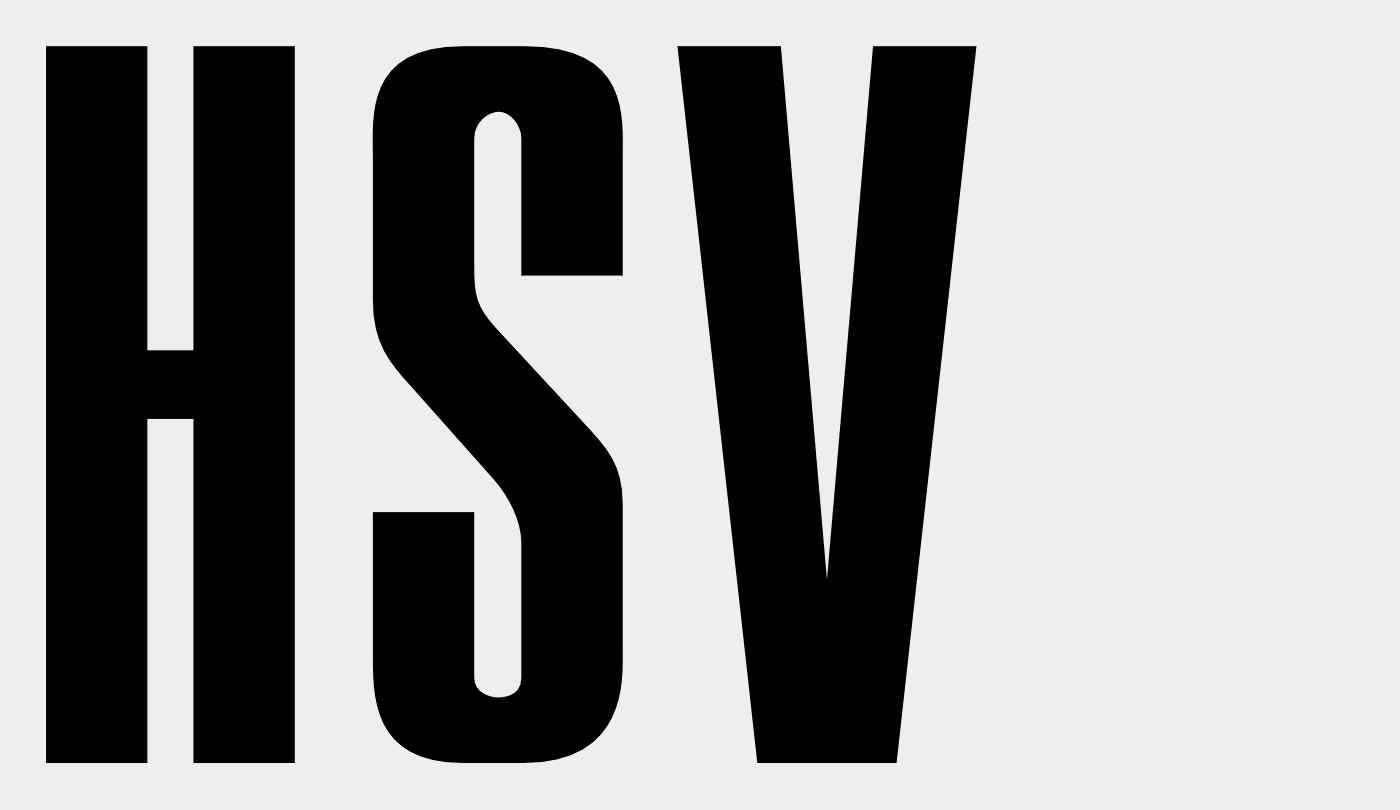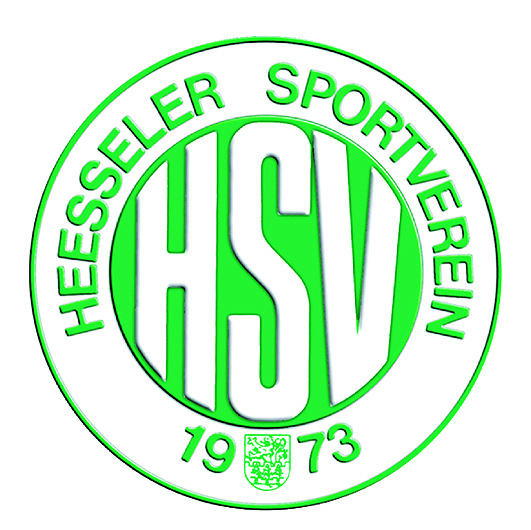
Suche Schriftart/en aus Heeßeler SV Logo
Hallo, ich darf/soll das Logo eines Sportvereins nachsetzen, da es nur als jpg existiert :o( Kann mir jemand verraten, um welche Schriftart es sich in der Mitte des Logos ("HSV") handelt? Gern nehme ich auch einen Hinweis für die äußere Schrift, wobei ich da annehmen, dass es sich um eine Arial handeln kann...
Hallo! Eine Arial ist das garantiert nicht. Im Rundsatz ist es eine Helvetica Bold. In der Mitte tippe ich mal auf eine Helvetica Inserat.
Der Rundsatz ist aus einer Helvetica Regular, den Unterschied zur Arial sieht man in dem Beispiel am besten an der "1".
Für HSV könnte man eine Compact zugrunde legen …